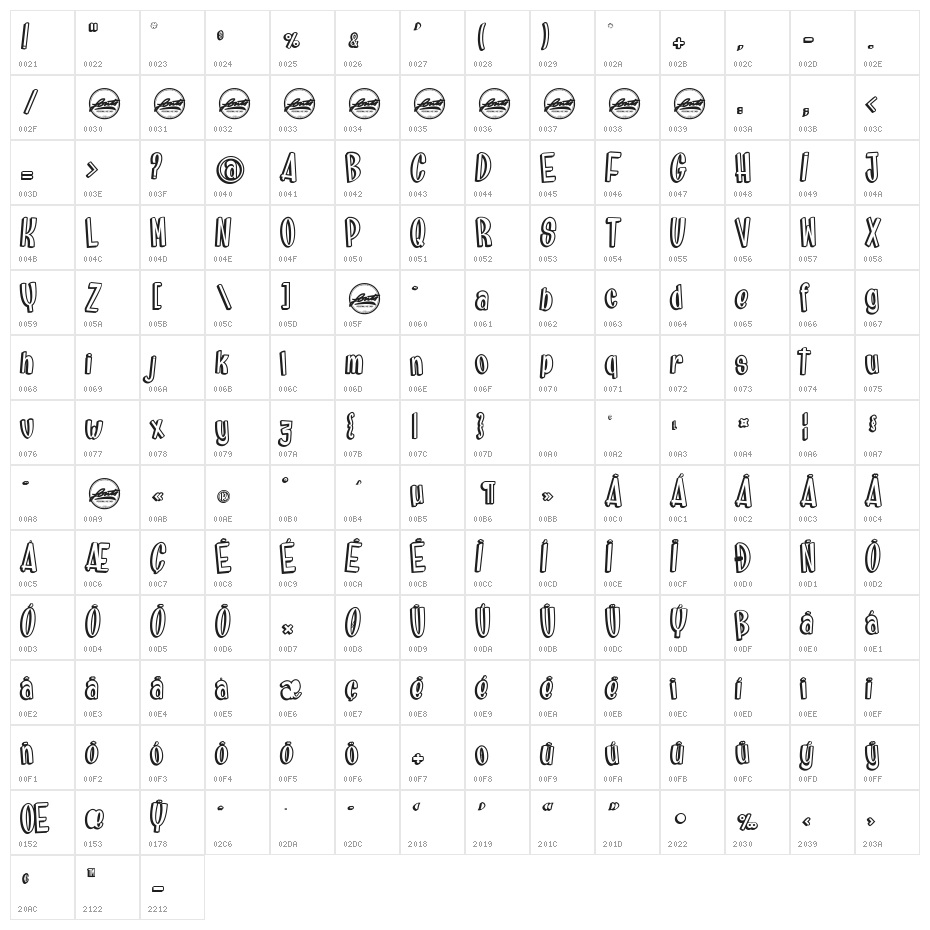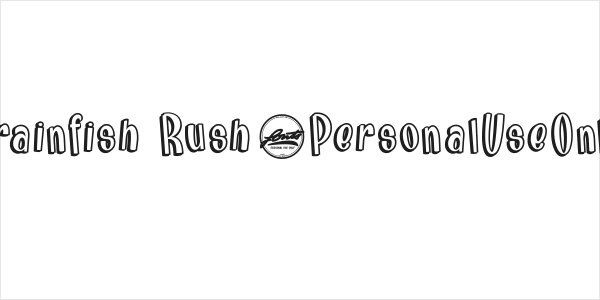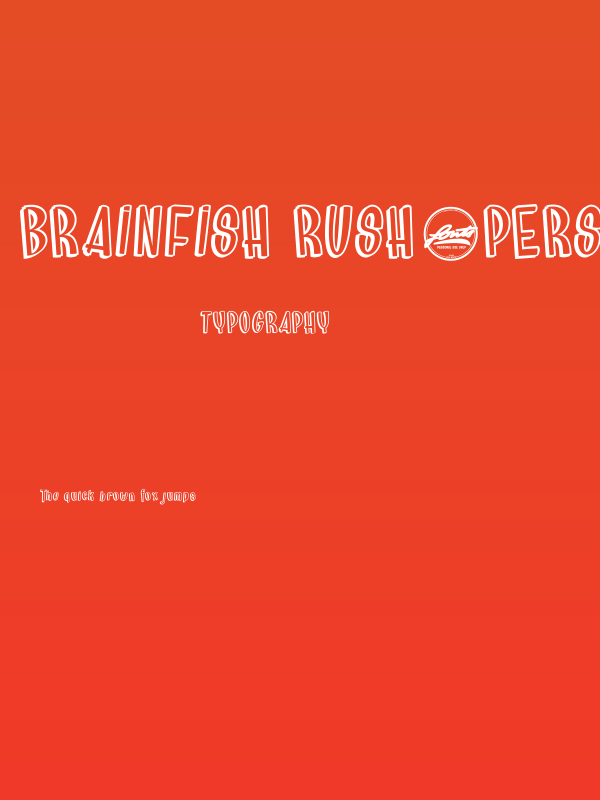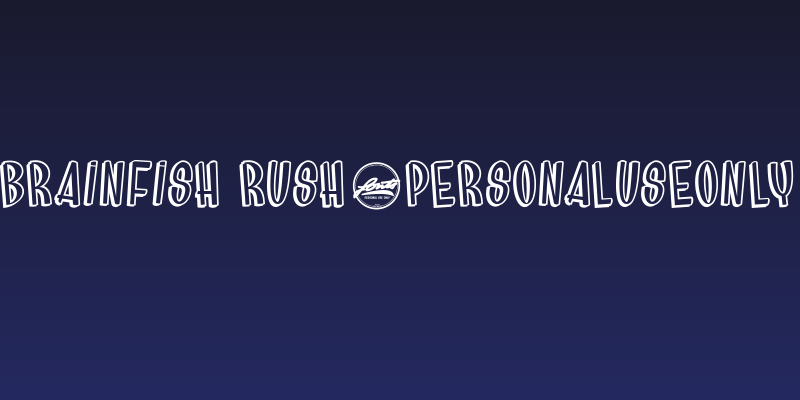
Brainfish Rush_PersonalUseOnly Font
| Stile generale | Playful, Cartoonish, Energetic |
| Progetti proposti | Ideal for children's book covers, playful branding, posters, and event flyers. |